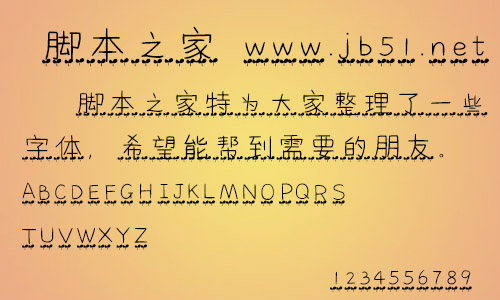
你是我的小葉子是一款電腦中文字體,字體文件格式為ttf。在每一個字的下面,都會有一片片小葉子,看起來十分清新的感覺。持漢字、符號、字母等。需要的朋友可以前來本站下載。
字體特色
--手機字體是仿照兒童手寫風(fēng)格的卡通手寫字體,結(jié)構(gòu)帶有POP字體風(fēng)格!
--下面還配上了非常有趣的卡通圖案做襯線,特別適合喜歡個性字體的用戶使用編輯!